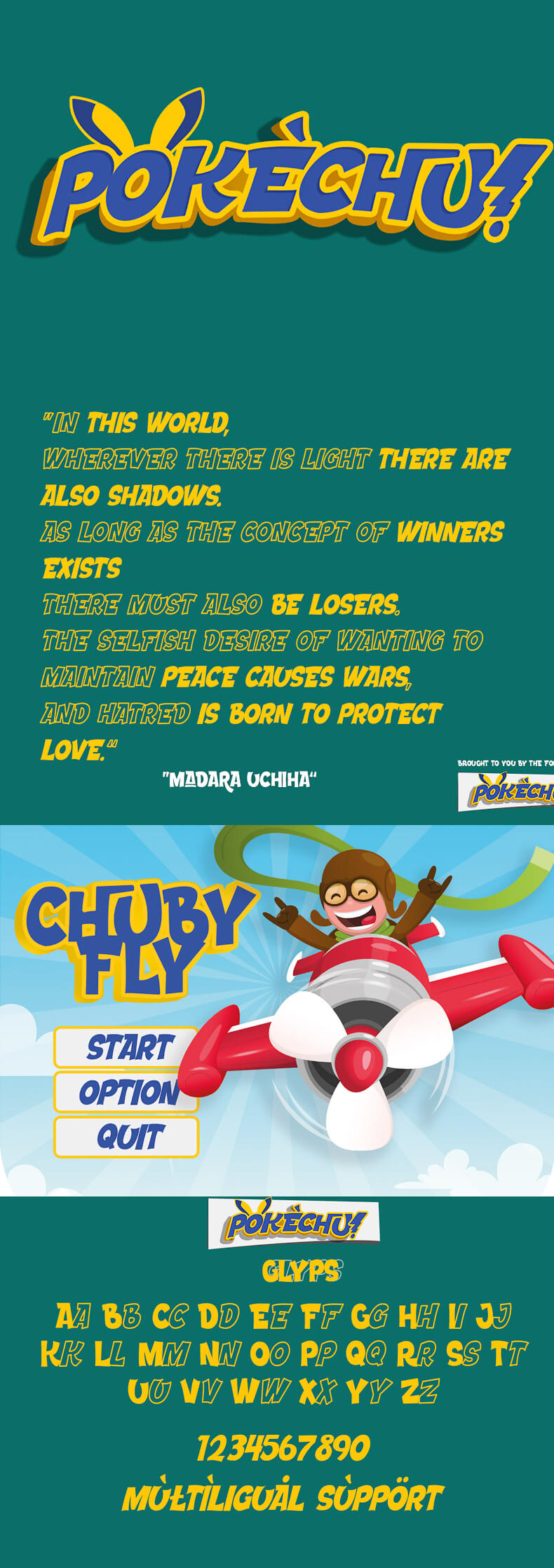
Шрифт - Pokechu
Шрифт Pokechu имеет строгий стиль, но при этом производит веселое впечатление, что позволяет легко читать и применять его во всех дизайн-проектах, таких как: плакаты, одежда, логотипы, цитаты, обложки альбомов, книги, визитные карточки, дизайн продуктов и многое другое. Поддержка латиницы.